Stylische Namens-Schriftarten sind spezielle Textstile (z. B. fett, kursiv oder dekorativ), die deinen Namen visuell hervorheben. Auf Facebook werden dafür keine echten Schriftarten genutzt, sondern sogenannte Unicode-Zeichen, die wie unterschiedliche Fonts aussehen.
Auf Facebook spielt dein Name eine zentrale Rolle. Er ist oft das Erste, was andere Nutzer sehen – egal ob im Profil, in Kommentaren oder im Newsfeed.
Die erste Wahrnehmung entsteht in wenigen Sekunden. Ein klarer und auffälliger Name kann sofort Interesse wecken und dafür sorgen, dass dein Profil nicht übersehen wird.
Visuell gestaltete Namen mit stylischen Schriftarten ziehen mehr Aufmerksamkeit an. Sie heben sich vom Standard ab und helfen dir, im Feed schneller aufzufallen.
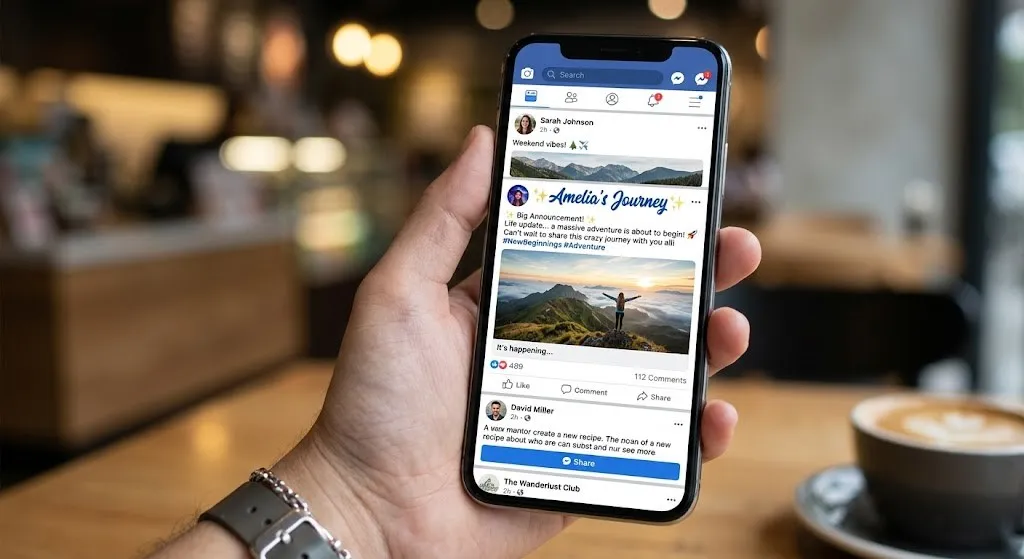
Warum stylische Schriftarten für Facebook-Namen wichtig sind
Stylische Schriftarten auf Facebook sind mehr als nur Design – sie helfen dir, Aufmerksamkeit zu gewinnen und deine Persönlichkeit sichtbar zu machen.
Aufmerksamkeit & Differenzierung
Im überfüllten Feed fallen besondere Schriftarten sofort auf. Sie sorgen dafür, dass dein Name nicht untergeht und Nutzer eher hinschauen.
Persönliche Marke (Branding)
Eine einzigartige Schrift unterstützt dein Personal Branding. Sie zeigt deinen Stil und hilft dir, dich von anderen Profilen zu unterscheiden.
Wiedererkennungswert
Ein stylischer Name bleibt besser im Kopf. Nutzer erkennen dich schneller wieder, besonders bei Kommentaren oder Beiträgen.
Emotionale Wirkung von Schrift
Schriftarten vermitteln Gefühle – elegant, stark oder kreativ. So wird dein Name zu einer visuellen „Stimme“, die deine Persönlichkeit ausdrückt.
Wie funktionieren Facebook Schriftarten technisch?
Auf Facebook gibt es technisch gesehen keine echten, frei wählbaren Schriftarten. Stattdessen basiert alles auf System-Fonts und Unicode-Tricks.
Unicode vs. echte Fonts
Die normalen Schriftarten auf Facebook werden über System-Fonts (CSS) gesteuert.
„Stylische“ Schriftarten hingegen sind keine echten Fonts – sie bestehen aus Unicode-Zeichen, die wie andere Buchstaben aussehen (z. B. 𝓐, 𝔄, 𝗔).
👉 Diese werden einfach kopiert und eingefügt
Warum Facebook keine Fonts erlaubt
Facebook nutzt standardisierte Schriftarten, um:
- schnelle Ladezeiten zu gewährleisten
- Lesbarkeit auf allen Geräten sicherzustellen
- ein einheitliches Design zu behalten
👉 Deshalb sind echte Schriftart-Änderungen nicht möglich
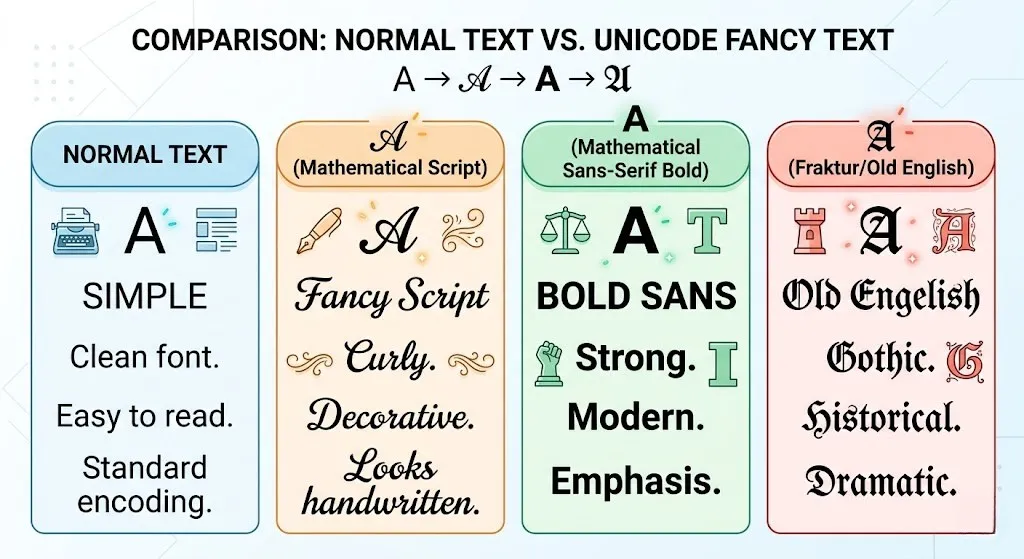
Darstellung auf verschiedenen Geräten
Unicode-Schriftarten werden meist auf allen Geräten angezeigt (Android, iOS, Desktop).
Aber:
- Manche Zeichen sehen unterschiedlich aus
- Einige Fonts werden nicht korrekt dargestellt
👉 Wichtig: Immer einfache und gut lesbare Styles wählen
Die besten Schriftarten für Facebook-Namen
Für stylische Namen auf Facebook werden meist sogenannte fancy fonts (Unicode-Zeichen) genutzt. Sie helfen dir, deinen Namen visuell hervorzuheben und einzigartig zu machen.
Auffällige & fette Schriftarten
Diese Schriftarten ziehen sofort Aufmerksamkeit an:
- 𝗦𝘁𝘆𝗹𝗶𝘀𝗵 𝗡𝗮𝗺𝗲
- 𝑺𝒕𝒚𝒍𝒊𝒔𝒉 𝑵𝒂𝒎𝒆
👉 Ideal für starke Botschaften und maximale Sichtbarkeit
Minimalistische & cleane Fonts
Einfach und gut lesbar – perfekt für einen professionellen Look:
- 𝚂𝚝𝚢𝚕𝚒𝚜𝚑 𝙽𝚊𝚖𝚎
- Sans-Serif Styles
👉 Klar, modern und angenehm zu lesen
Kreative & dekorative Schriftarten
Diese Fonts sind verspielt und besonders auffällig:
- 𝓢𝓽𝔂𝓵𝓲𝓼𝓱 𝓝𝓪𝓶𝓮
- ꧁༺ Stylish Name ༻꧂
👉 Perfekt für kreative und einzigartige Profile
Wie man stylische Facebook-Namen erstellt
Einen stylischen Namen auf Facebook zu erstellen ist einfach, wenn du die richtigen Tools und Methoden nutzt.
Mit Tools wie Creative Fabrica oder LingoJam kannst du deinen Namen in verschiedene Schriftarten umwandeln:
- Namen eingeben
- Stil auswählen (fett, kursiv, fancy)
- Ergebnis generieren
👉 Schnell und ohne Designkenntnisse
Copy & Paste Methode
Die einfachste Methode:
- Generierten Namen kopieren
- In Facebook (Name, Bio oder Info) einfügen
👉 Funktioniert direkt und ohne Aufwand
Kombination mit Symbolen & Emojis
Du kannst deinen Namen zusätzlich mit Symbolen aufwerten:
- ★Name★
- ⚡Name⚡
- 『Name』
👉 Macht deinen Namen noch auffälliger und einzigartig
Beispiele für stylische Facebook-Namen
Stylische Namen auf Facebook entstehen durch kreative Kombinationen, moderne Begriffe und persönliche Elemente. Hier sind einige Ideen:
Coole Namen
- TechWizard
- MoonWalker
- LivingLegend
- MindOverMatter
👉 Modern, stark und auffällig
Ästhetische Namen
- BohoBella
- UrbanAura
- WanderLuxus
Trends sinnvoll nutzen
Orientiere dich an aktuellen Trends, aber übertreibe es nicht. Wähle nur das, was zu deinem Stil passt.
Fazit
Bei stylischen Namen auf Facebook kommt es vor allem auf die richtige Balance an. Kreativität ist wichtig, aber sie sollte niemals die Lesbarkeit beeinträchtigen.
Setze auf einen klaren, einheitlichen Stil, der deine Persönlichkeit oder Marke widerspiegelt. So bleibt dein Name nicht nur auffällig, sondern auch leicht verständlich.